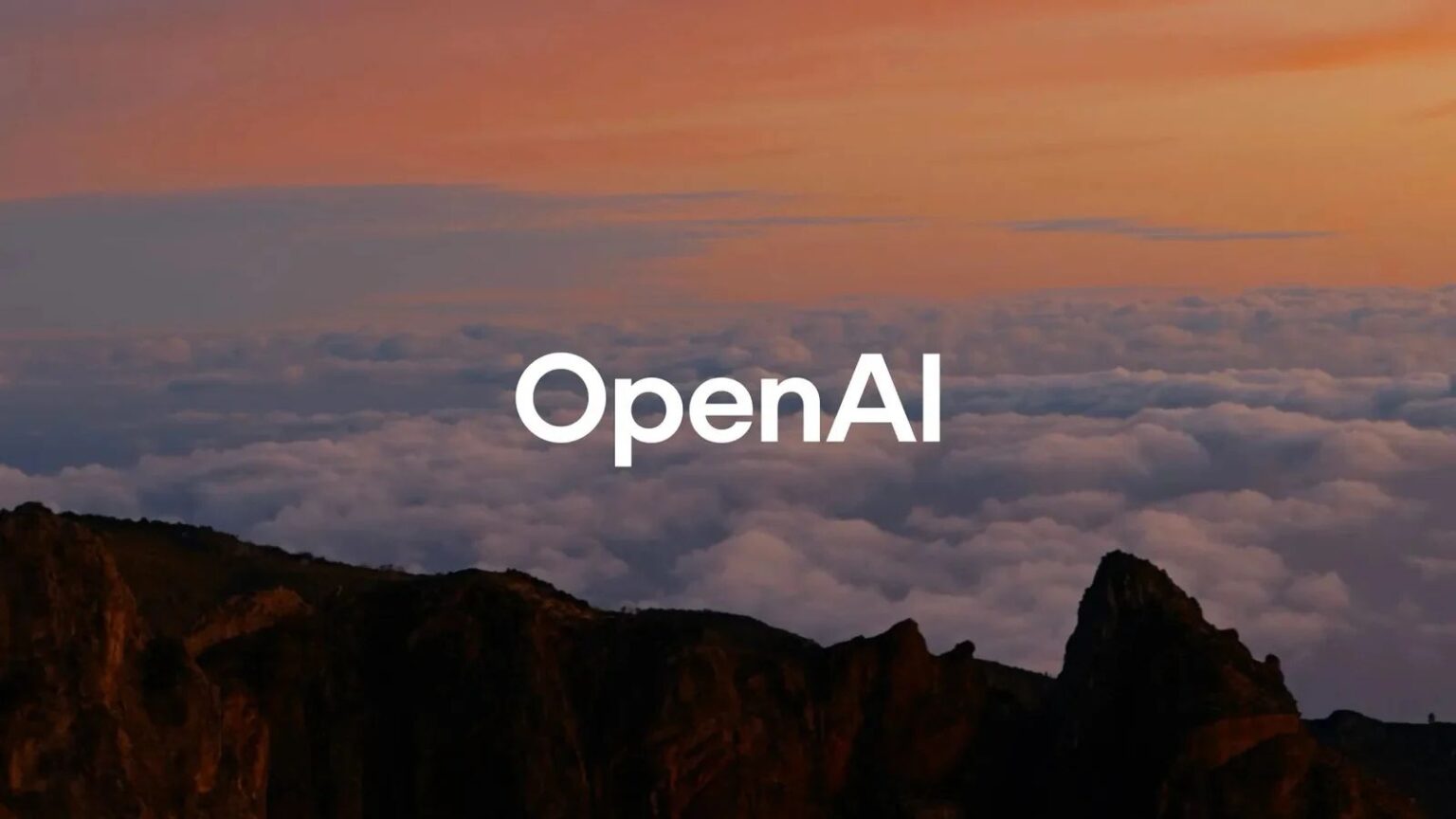
È arrivato il momento di una profonda modifica almeno sul lato visivo per OpenAI. Secondo quanto riportato ufficialmente infatti il colosso dell’intelligenza artificiale ha modificato il logo ed ha introdotto anche un nuovo font personalizzato. Oltre a queste modifiche, ecco anche nuovi colori aggiornati, tutto adopera di esperti del calibro di Veit Moeller e Shannon Jager. L’intento principale è quello di avvicinarsi quanto più possibile agli esseri umani.
Un logo rinnovato, ma familiare: così cambia OpenAI
Il nuovo logo non stravolge l’iconico “blossom” (fiore), originariamente disegnato dal CEO Sam Altman e dal co-fondatore Ilya Sutskever, ma ne affina le linee per renderlo più pulito e armonioso.
Le modifiche sono quasi impercettibili:
- Lo spazio centrale è più ampio, migliorando l’equilibrio visivo;
- Le linee risultano più nette e definite, conferendo al logo un aspetto più moderno e maturo.
Si tratta di piccoli dettagli, che però riflettono l’evoluzione dell’azienda e la sua crescita nel settore AI.
OpenAI Sans: il nuovo carattere tipografico
Un altro grande cambiamento è l’introduzione di OpenAI Sans, un carattere tipografico personalizzato, studiato per bilanciare precisione geometrica e accessibilità visiva.
Nel nuovo wordmark di OpenAI, la lettera “O” è stata ridisegnata con un esterno perfettamente circolare, mentre l’interno mantiene un’imperfezione volutamente umana. Secondo Moeller, questa scelta serve a contrastare la rigidità robotica e a trasmettere un senso di calore e naturalezza.
AI e creatività: un equilibrio tra umano e macchina
Nonostante OpenAI sia leader nello sviluppo di strumenti AI come ChatGPT e DALL·E, il team di design ha scelto di usare l’intelligenza artificiale solo in modo limitato per il rebranding.
Gli strumenti AI sono stati impiegati principalmente per calcolare i pesi tipografici, mentre il processo creativo è rimasto salda espressione dell’intuizione umana.
Come spiegato dai designer alla testata Wallpaper:
“Collaboriamo con esperti di fotografia, tipografia, motion e design spaziale, integrando strumenti AI come DALL·E, ChatGPT e Sora come partner di pensiero. Questo approccio duale – dove l’intelligenza umana incontra il potenziale dell’AI – ci permette di creare un brand non solo innovativo, ma profondamente umano.”